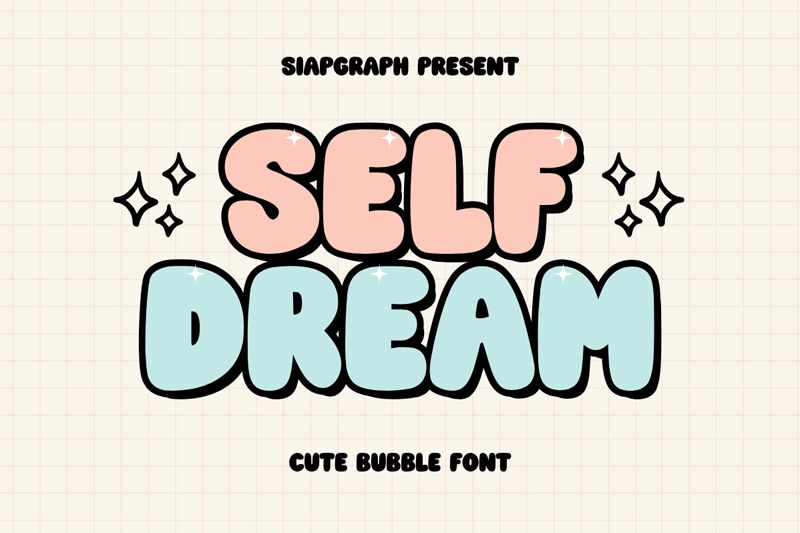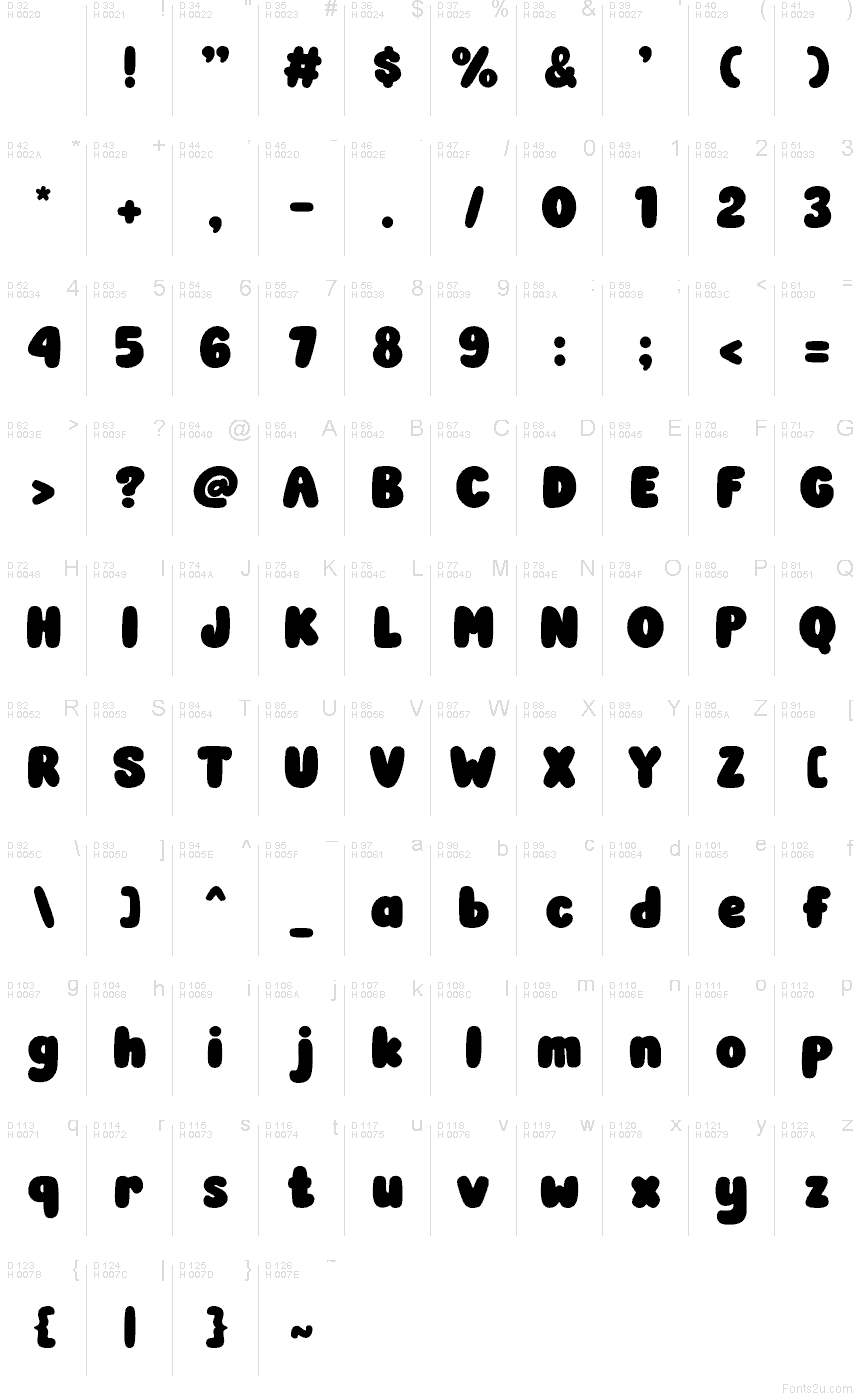
Self Dream
يعد Self Dream من SIAPGRAPH STUDIO خط عرض (Display) مجاني بنمط كرتوني، مصمم بملامح دائرية كبيرة ومنحنيات ناعمة ومنفوخة. تبدو الحروف كأنها سلسلة من الأشكال السوداء الممتلئة، مما يضفي على التصميم طابعاً مرحاً وحيوياً يشبه الألعاب، ويبدو أكثر احترافية وجرافيكية من كونه مرسوماً باليد.
هذا المظهر المكتنز والناعم يجعل من Self Dream خياراً طبيعياً لأغلفة كتب الأطفال، وعبوات الوجبات الخفيفة، ودعوات أعياد الميلاد، وتصاميم الملصقات، والصور المصغرة الجذابة على يوتيوب. تستفيد العناوين القصيرة والشعارات من هذا الخط بشكل كبير، خاصة عندما تبحث عن حروف ودودة وبارزة يسهل تحويلها إلى عنصر بصري مركزي.